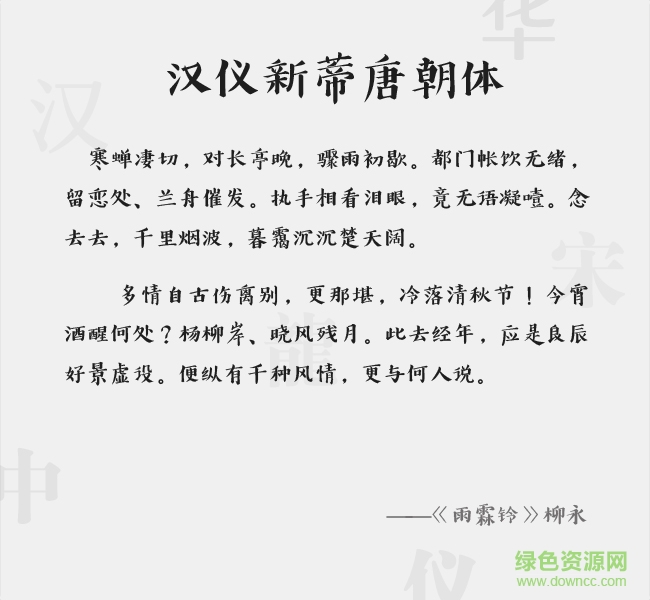
漢儀新蒂唐朝體是一款漢儀類古典文雅風格字體軟件,新蒂唐朝體一筆一畫一絲不茍,粗細相間,優(yōu)雅氣息十足,還有更多類似好看字體歡迎來綠色資源網(wǎng)下載體驗!
漢儀新蒂唐朝體是一款應用于藝術(shù)設(shè)計方面的簡體中文字體,該字體筆畫粗壯,尾部的甩尾有力且有豐富的筆觸細節(jié),大字效果突出且引人注目;并且最大程度還原作者書寫字形,細節(jié)表現(xiàn)完整,且字庫完整,可以廣泛應用于名片設(shè)計、新聞媒體、宣傳海報、ppt、影視制作以及內(nèi)容用字等領(lǐng)域。
該字體橫細豎粗,非常的文雅脫俗,整體效果十分酷炫好看,盡顯書法大師的魅力,用來??嵩俸线m不過了!